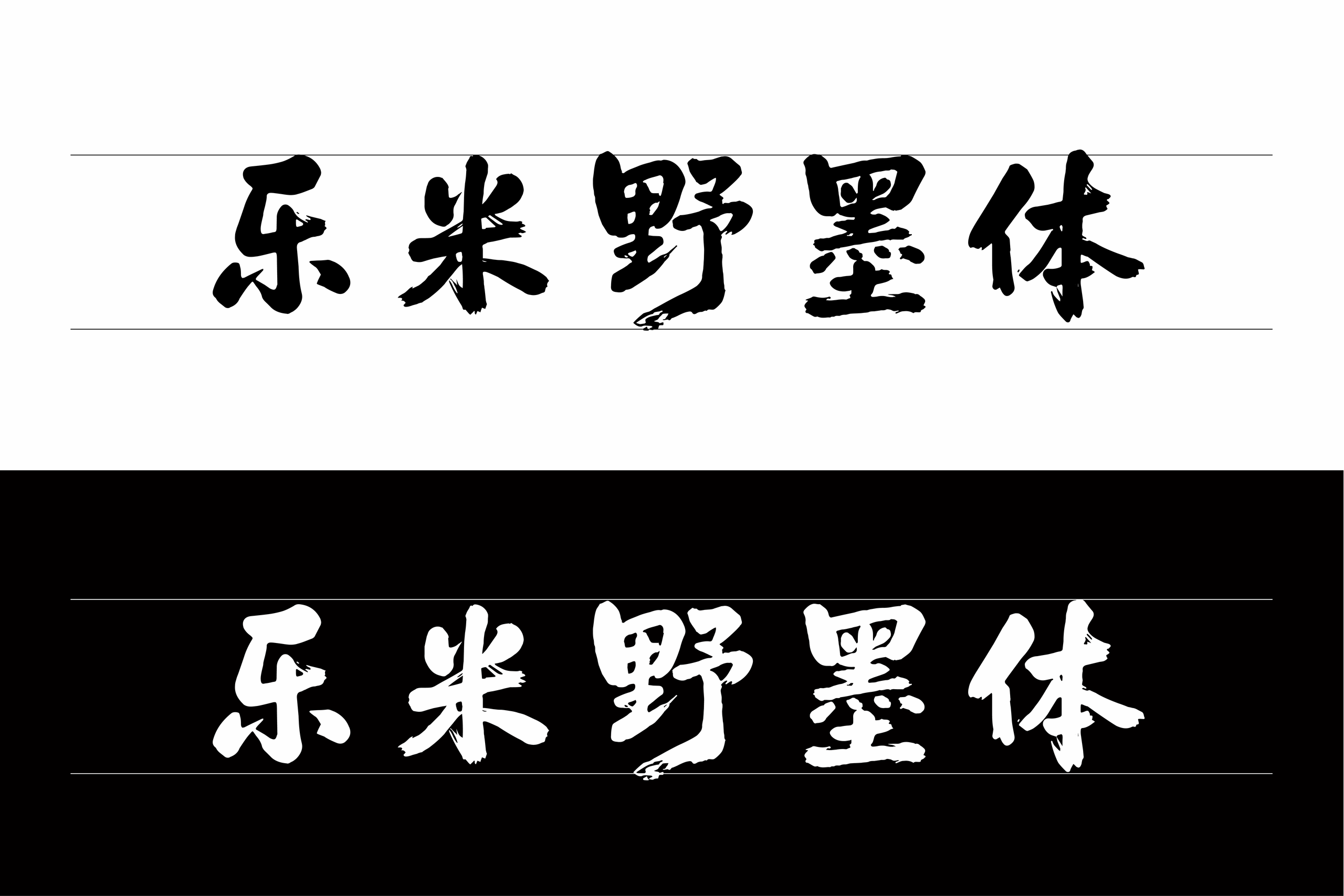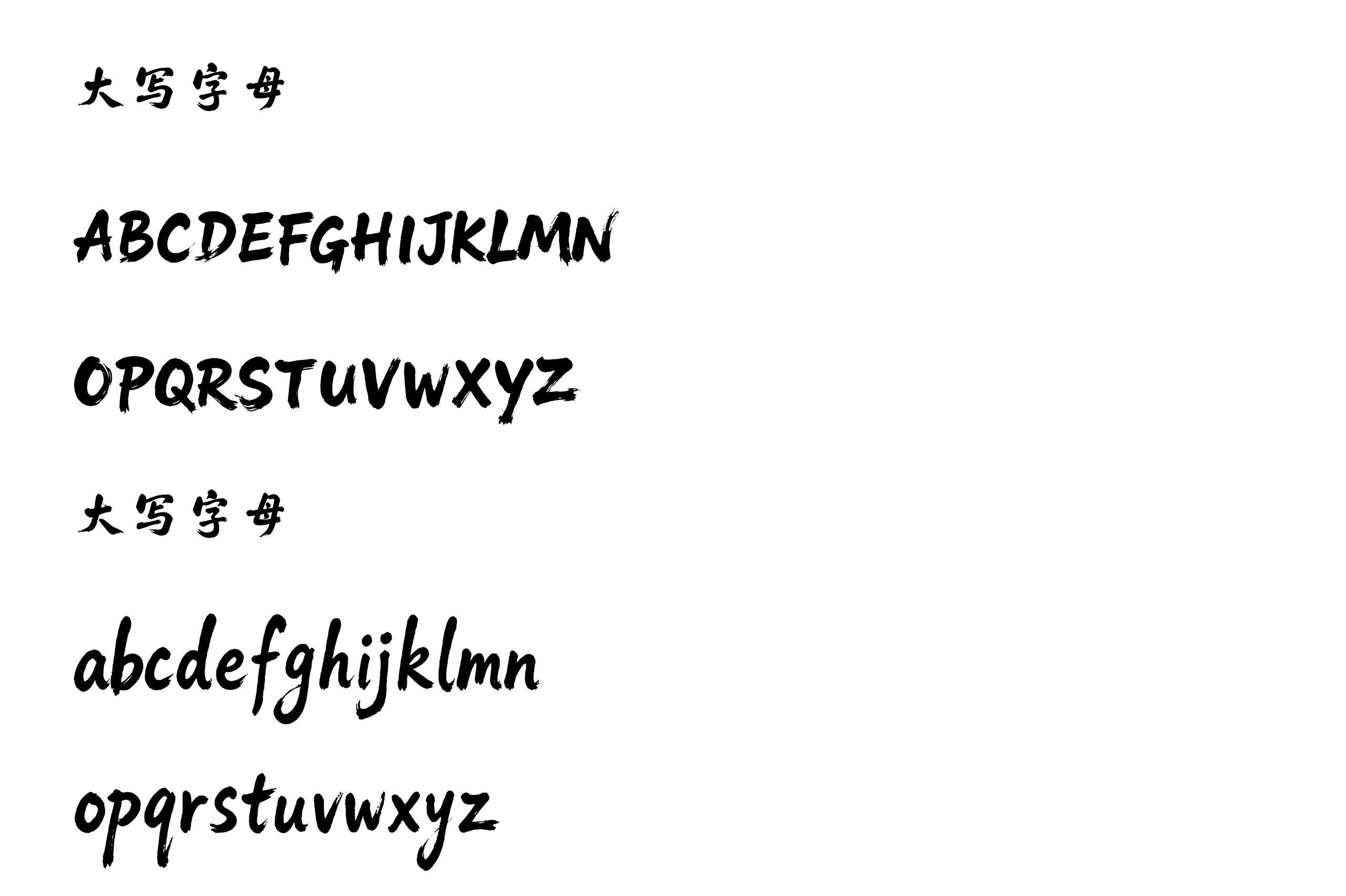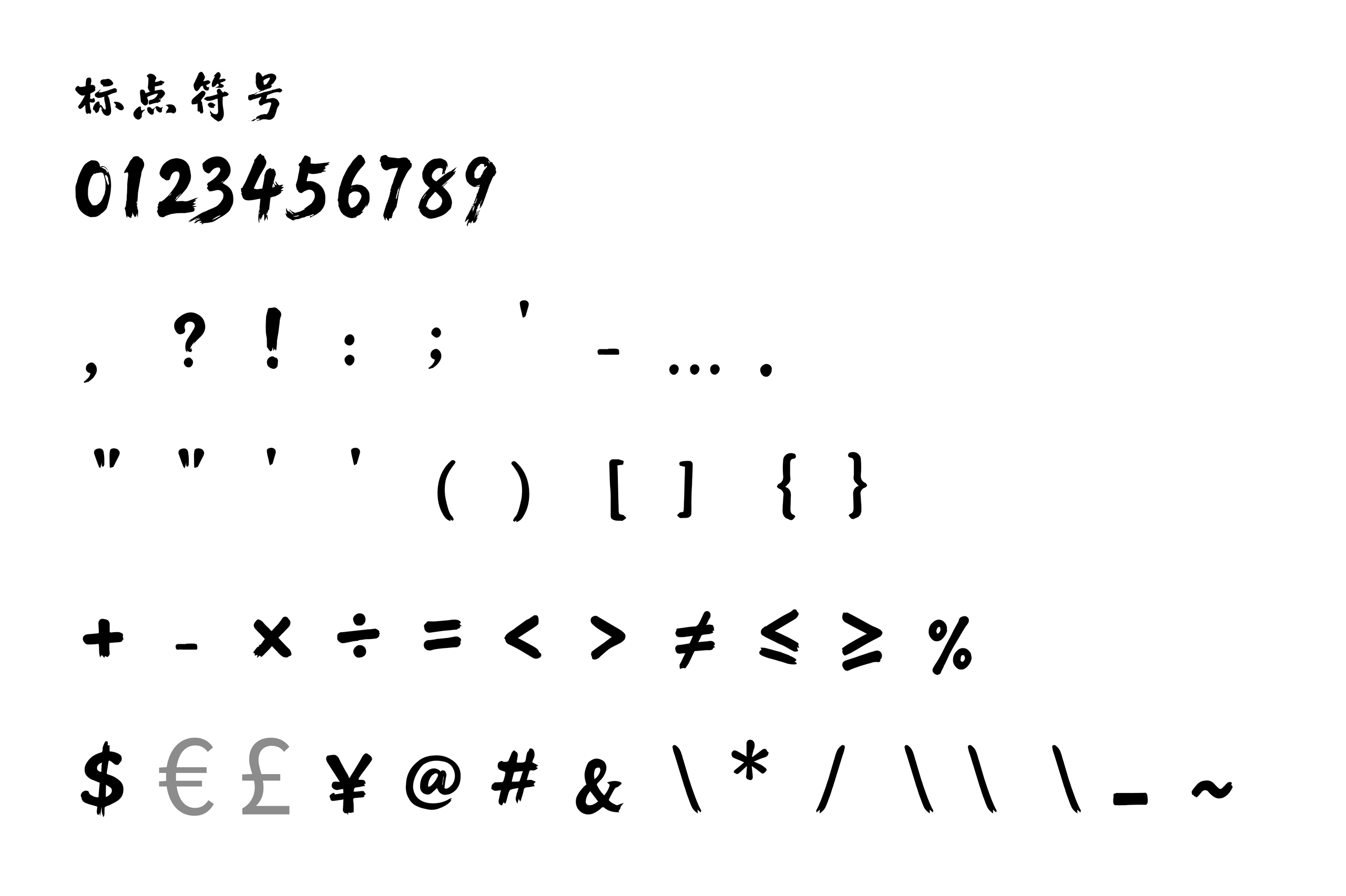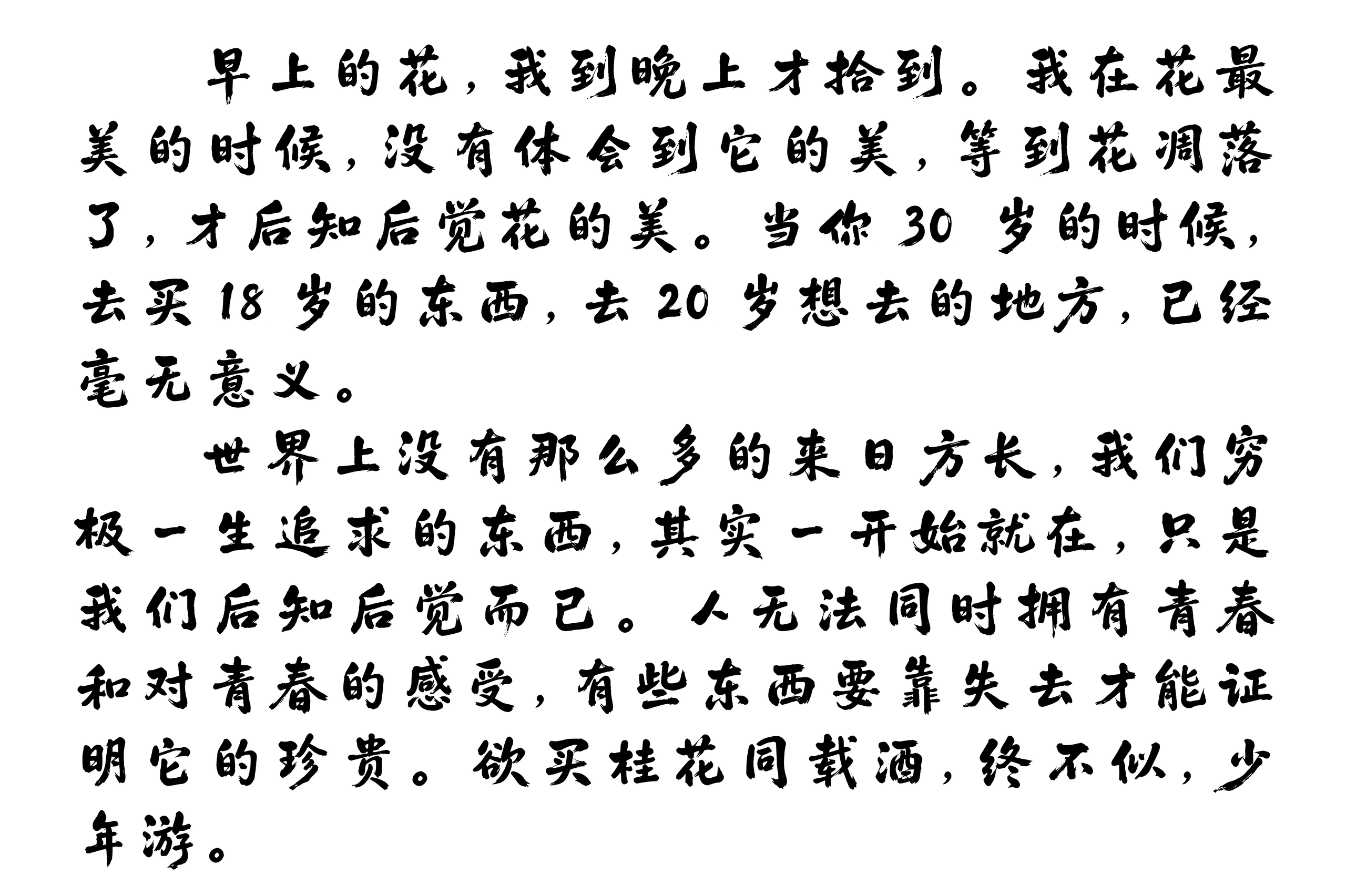
乐米野墨体
乐米野墨体是一款由杭州乐米网络科技有限公司发布,并提供免费商用授权的中文字体。字体整体采用偏粗的手写笔触进行设计,字形中保留了明显的书写痕迹与墨迹质感,笔画起收之间带有自然的顿挫和飞白效果,相比规整的印刷字体,更具有手写书法的随性与力量感。
从字形表现来看,乐米野墨体的笔画较为厚重,部分笔画边缘带有自然的毛笔擦痕与墨迹变化,字形并没有刻意追求工整统一,而是保留了一定的手写随机感。尤其是在横、撇、捺等笔画中,可以看到明显的笔锋变化,使文字呈现出较强的动态感和视觉张力。
中文部分整体属于粗笔手写风格,既有传统毛笔字的书写韵味,也融入了较为直接、现代的视觉处理。字体用于大字号展示时,粗壮的笔画和不规则的墨迹边缘能够形成比较突出的视觉效果,适合用于需要强调手作感、力量感或传统文化气息的设计场景。
除了中文字符外,乐米野墨体还配有完整的英文字母,包括大小写字母。英文字形同样延续了中文部分的手写笔触,字母轮廓具有明显的毛笔书写特征,并加入了一些自然的笔锋变化。在中英文混排时,整体风格能够保持较好的统一性。
字体同时包含数字以及常用标点、数学符号和货币符号等字符,可以满足海报标题、宣传文案、包装文字、封面设计以及社交媒体图片等常见视觉设计需求。由于字体本身具有较强的个性化特征,更适合作为标题、短句和重点文字使用,不太适合大段正文阅读。
从实际展示效果来看,乐米野墨体比较适合用于国风海报、书法主题设计、餐饮包装、文化活动宣传、品牌视觉、短视频封面以及具有手作气质的标题设计。粗犷的笔触能够增强画面的视觉重量,而自然的墨迹变化又可以避免文字显得过于机械,非常适合需要突出手写感的设计作品。